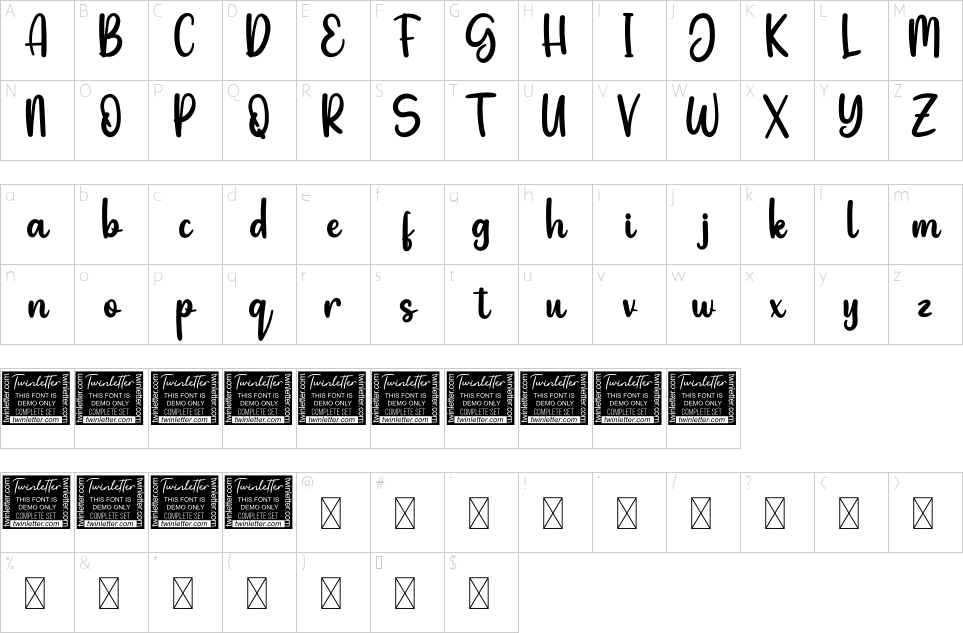
Astringe Font – Fonte Grátis
Astringe Font
A Astringe é uma fonte que oferece uma paleta de linhas sutis e elegantes, perfeita para escritas de texto leve e agradáveis aos olhos. Com seu design cuidadosamente pensado por rozi, esta fonte foi projetada para complementar e iluminar qualquer projeto de design. Sua simplicidade e elegância fazem da Astringe uma escolha inteligente para aplicativos que exigem uma aparência minimalista e harmoniosa. Disponível tanto para Windows quanto para Mac, Astringe é uma fonte gratuita que merece ser usada em qualquer projeto de design gráfico que busca uma aparência atraente e sofisticada. Seja para criar materiais de marketing, design editorial ou até mesmo para estilos de blog, a Astringe é uma ótima opção para quem busca uma fonte de qualidade para seu trabalho.
Mapa de caracteres da fonte Astringe Font